如何在 WordPress 網站上使用可變字體
什麼是可變字體?
可變字體是單個字體,CSS 可以根據 5 個不同的標准或軸來更改這些字體。 每個軸控製字體外觀的一個特定方面,並具有相應的 CSS 標籤。
- 重量(CSS 中的wght )
- 傾斜(CSS 中的slnt )
- 斜體(ITAL在CSS)
- 光學尺寸(CSS 中的opsz )
- 寬度(CSS 中的wght )
然後是偽軸 Grade,在 CSS 中用GRAD表示。 我希望我能告訴你為什麼在你的樣式表中使用 Grade 時用全大寫寫......但我不能。 就是這樣。 此外,隨著技術的發展,不同的公司可以引入(並且正在)新的軸。 因此,我們將來可以用這些來做很多事情。
當組合所有這些不同的軸時,您可以使任何單個字體大致做您想做的任何事情——甚至像 SVG 一樣為它們設置動畫。 (請注意,這也包括像我們這樣的圖標字體。)
為什麼要使用可變字體?
簡短的回答是他們比嵌入和您的網站上呈現多種字體更為有效。 谷歌的開發者文檔總結得很好:
OpenType 可變字體允許我們將類型系列的多個變體存儲到單個字體文件中。 Monotype 進行了一項實驗,通過組合 12 種輸入字體來生成 8 個權重,跨越三種寬度,跨越斜體和羅馬風格。 在單個可變字體文件中存儲 48 種獨立字體意味著文件大小減少了88% 。 (強調他們的)
在 WordPress 中使用可變字體
所以現在我們知道可變字體非常棒,下一步是將它們整合到我們的工作流程和 WordPress 網站中。
第1步
您要做的第一件事是在您的網站上安裝字體。 您可以使用像 Use Any Font 這樣的插件,如果您是 ET 成員,則可以直接通過 Divi 界面上傳,使用@font-face 鏈接到它,或者完全放棄插件和主題並以老式的方式進行。
不管你怎麼做,一旦你把它放在你的網站上,使用這種字體實際上很容易。 為此,我通過 Divi 上傳了免費字體 Gingham,因為這就是我使用的。 最終結果是一樣的。
第2步
由於可變字體是基於 CSS 的,因此您將想要轉到添加自定義 CSS 的任何位置。 這可能在custom.css文件、 stylesheet.css 、WordPress 定制器的附加CSS 中,甚至在 Divi 主題選項的常規選項卡的底部(大多數主題也有類似的框)。 您將輸入此代碼(使用您正在使用的任何可變字體的名稱)。
}它在您的 CSS 窗口中看起來像這樣。
所有這些都是允許您在您的網站上使用字體。
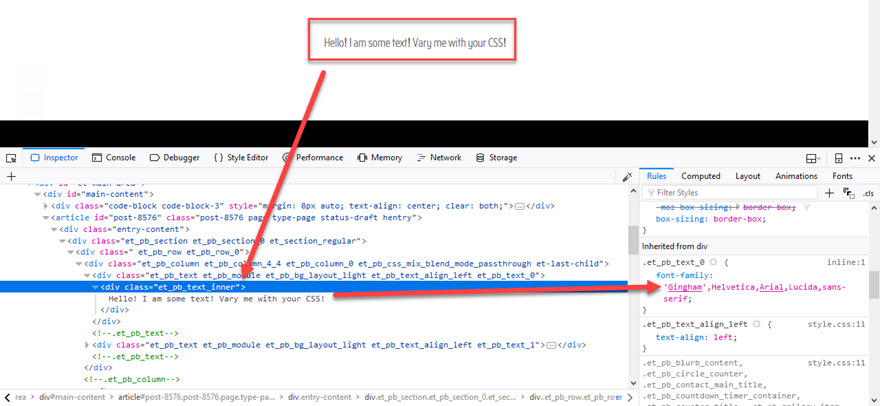
第 3 步
現在是時候以某種方式設計它了。 你可以用它做任何你想做的事情,樣式可以應用於任何類或 ID。 正如你所看到的,這個被應用於任何.et_pb_text div。 您可以將它應用於全身或h1、h2、h3甚至p。 你的選擇。 畢竟它們是可變字體。
有兩種方法可以解決這個問題。 第一個是使用font-variation-settings的單個高效 CSS 行。
}您也可以將這些添加到其他 CSS 中,就像浮動或z 軸或其他任何東西一樣。
或者,您可以在單獨的行上輸入軸。
他們最終都做同樣的事情。
我在哪裡可以找到可變字體?
找到可變字體比僅僅使用 Google Fonts 稍微困難一些(尤其是因為沒有一個 Google Fonts 是可變的)。 因為這項技術是新的,可變字體並沒有那麼普遍。 由於軸之間的所有交互,它們必須單獨製作,因此在提供它們的地方,它們通常是購買的優質字體。
免費可變字體
也就是說,您可以獲得一些免費的個人字體。 這些是品味高雅且總是才華橫溢的肯尼·辛(Kenny Sing)推薦的。
- 格子就是我們上面使用的。 肯尼讓我參與其中,這是一個很好的選擇。
- League Mono 也是簡單但多功能的可變字體的不錯選擇。
- 雷納的頁面說這是一部現代傑作。 我有什麼資格爭論?
現在應該可以了。 因為可變字體就像一個盒子裡裝了幾十種字體,下載上面的那些,你可以訪問更多的選項,我數不清。
記住